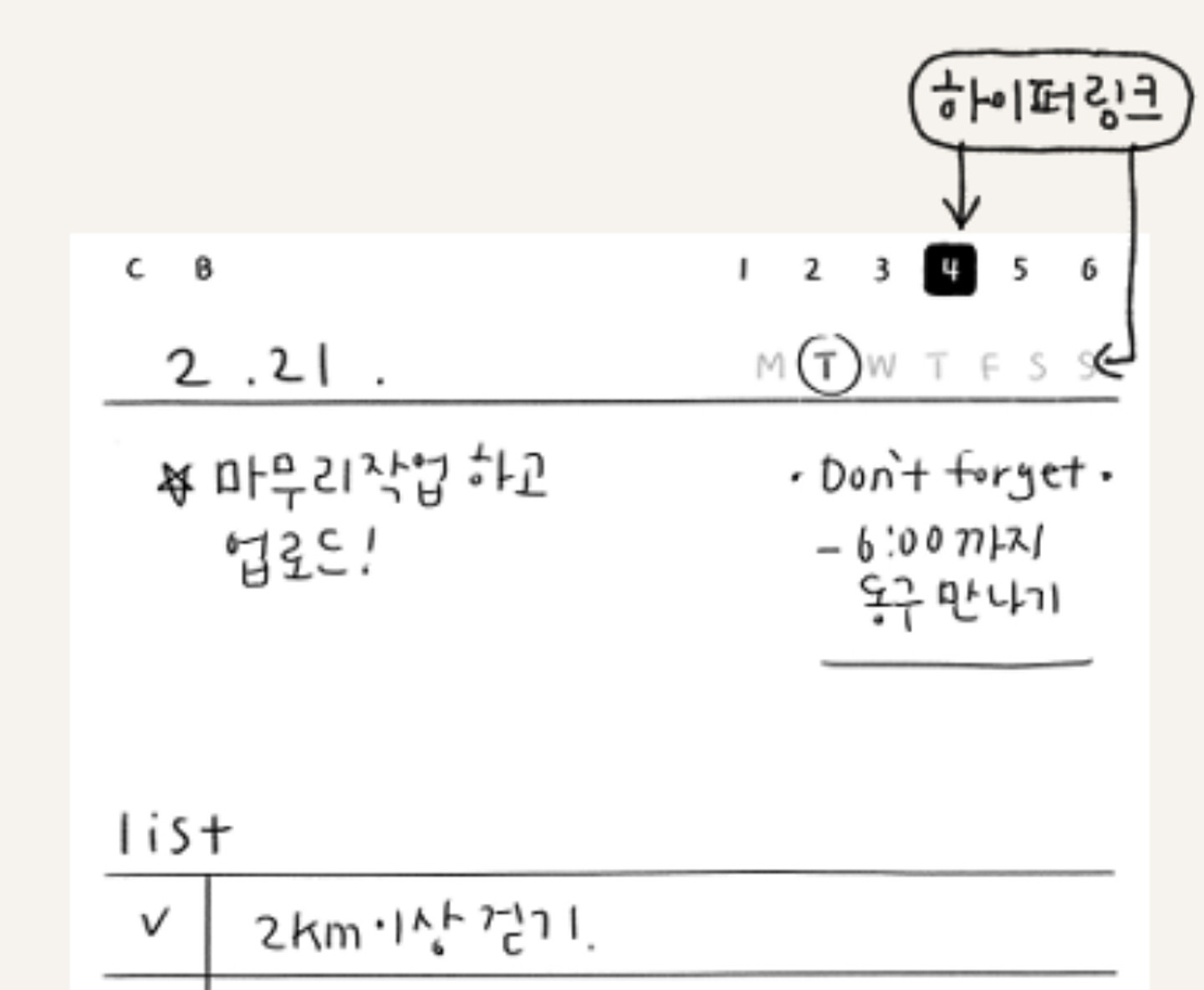
Navine Condensed Black
이텔릭으로 변형하여 사용한 것입니다요
이 폰트 HU하늘고딕 140로 알려주셨는데 느낌은 비슷하지만 히읗이 다르고 사진 속 폰트가 획이 더 긴 느낌이라 정확히 알려주실분 ㅜㅜ
헤이세이노트손글씨라고 써져있는데, 검색해도 나오질 않아서요. 무슨 폰트일까요? 제일 비슷한 일본어 폰트라도 알고 싶습니다.